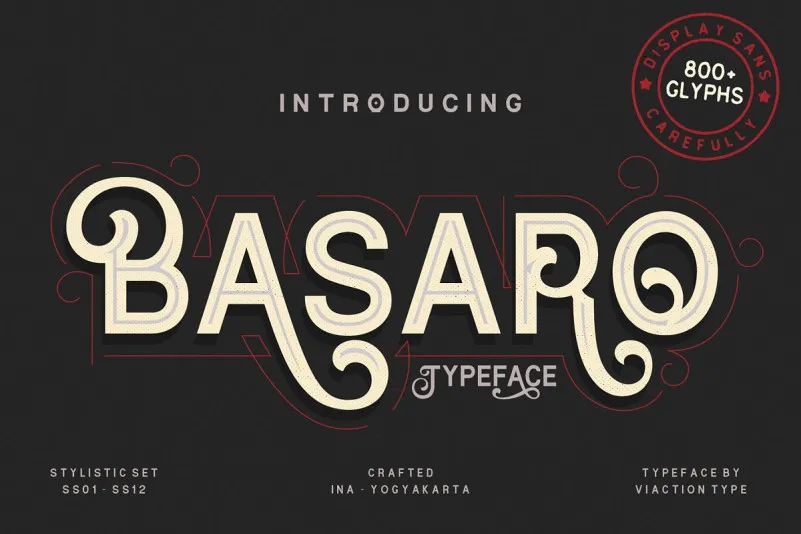
Basaro Display Font é uma elegante fonte serif que oferece uma mistura única entre modernidade e estilo orgânico. Inspirada no belo e clássico, essa fonte sans-serif totalmente maiúscula se destaca para aplicações como rótulos de embalagens, cartazes, camisetas de estampas personalizadas, ou mesmo para capas de postais. Com seu design clean e moderno, Basaro Display fornece um toque único que complementa bem as idéias mais sofisticadas e criativas. Esta fonte é especialmente perfeita para uso em cabeçalhos e identificações visuais, proporcionando um aspecto atraente e distintivo ao seu design final. Com os 12 conjuntos alternativos de estilosizativo (ss01 até ss12) disponíveis por cada letra, você tem uma ampla gama para personalizar e explorar as possibilidades criativas que essa fonte oferece. Basaro Display é perfeito tanto para aqueles que buscam um design limpo e moderno quanto para os amantes de elementos clássicos e artísticos em suas criações visuais.